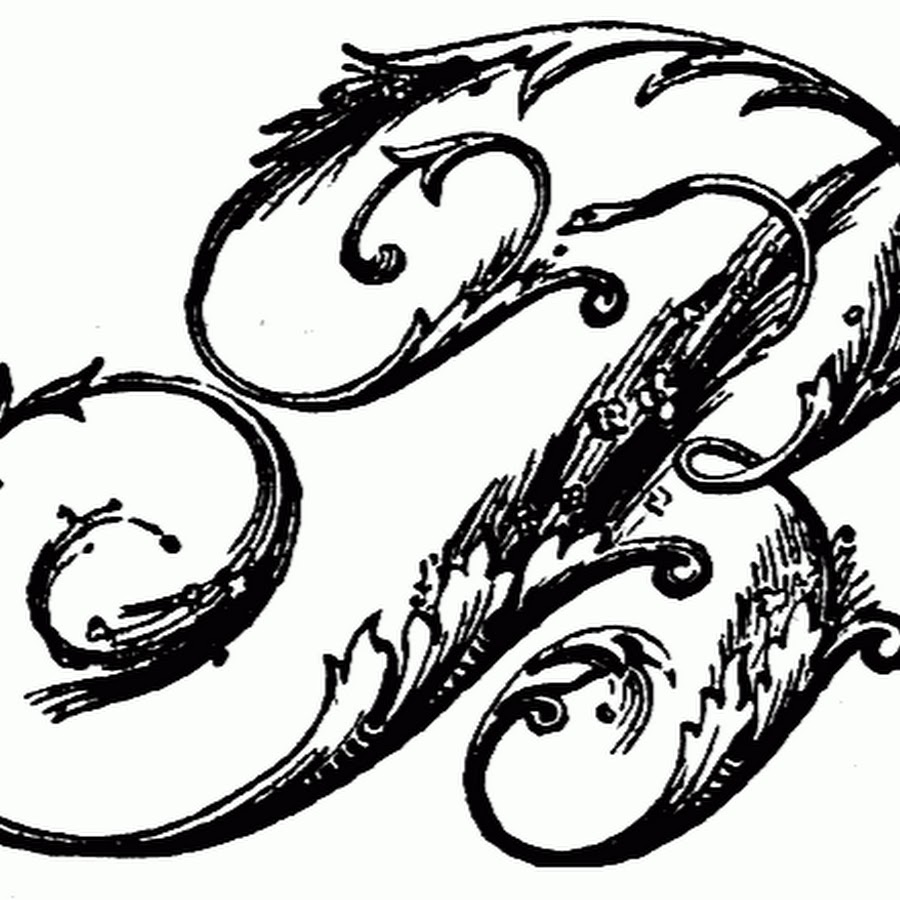
Вензельные шрифты русские: Рукописные русские шрифты
Русские декоративные шрифты XIX в.
* Шрифт 1812 года словолитни Лемана
Шрифт С. Чехонина * Инициальный шрифт С. Пожарского * Антиква орнаментированная * Обложка И. Кричевского
Инициальный шрифт Г. Фишера
Титульный шрифт С. Телингатера * Версалы О. Менхарта
Букман * Малый ленточный (Г. Кликушин)
Шрифт Б. Маркевича * Шрифт О. Менхарта * Оля (Г. Кликушин) * Обложка В. Милашевского
Антиква фигурная * Шрифт Виллу Тоотса
Витебский светлый (Г. Кликушин) * Витебский жирный (Г. Кликушин)
Витебский средний (Г. Кликушин)
Барс (Г. Кликушин) * Гранит (П. Кузанян) * Арабский * Обложка Н. Ильина
Украинский
Дракон (китайский) * Карнас * Нимфик * Титульный лист Д. Бисти
Ринглет
Бланшард * Юбилейный * Инициалы Г.
Кликушина * Суперобложка В. Фаворского
Давида
Орбита * Эксман * Велам * Обложка Г. Рифтина
Ориенте
Роберта * Гобо * Герольд (Н. Бертольд) * Итальянский (стилизация Г. Кликушина)
Чебурашка (Г. Кликушин)
Контдаун * Итальянский * Волна * Суперобложка В. Фаворского
Боттленек * Египетский декоративный
График (Э. Шнейдлер) * Пиноккио * Обложка Б. Шварца
Жетон
Увага (Г. Кликушин) * Фигурный (Г. Кликушин)
Сальто (К. Гофер)
Фигурный * Рукописный (Л. Раппопорт) * Каллиграфический * Обложка С. Пожарского
Каллиграфический
Рустика * Шрифт В. Воронецкого * Инициальный шрифт С. Телингатера * Л. Хижинский
Курсив И.
Жихарева (прописной) * Курсив И. Жихарева (строчной)
Лион курсив вензельный * Каллиграфический
Курсив вензельный
Импульс (П. Циммерман) * Бальзак (И. Бьёланд) * Шрифт Н. Пискарева * Обложка В. Лазурского
Шрифтовая композиция Виллу Тоотса
Дерби (Г. Ланге) * Шок * Дерби (прописной) * Дерби (строчной)
Антиква инициальная (Г. Кликушин)
Рондо * Шрифтовая композиция И. Гусевой
Рондо (П. Реэвеер) * Титульный лист С. Телингатера
Текст поздравительного адреса (X. Керсна) * Шрифтовая композиция Виллу Тоотса
Текст поздравительного адреса (П. Реэвеер)
Раффин (X. Кригер) * Курсив барокко (С. Кончев)
Текст поздравительного адреса (П. Лухтейн)
Каллиграфический (гарнитура) * Обложка К.
Ганнушкина
Манускрипт инициальный * Шрифтовая композиции Виллу Тоотса
Курсив * Тайм-скрипт (Г. Трумп) * Рваная кисть (Виллу Тоотс) * Обложка Виллу Тоотса
Редис
Экспресс (В. Гениш) * Редис сигнал
Редис курсив
Круглая кисть * Шрифтовая композиция Г. Кликушина * Солемнис * Обложка С. Телингатера
Круглая кисть
Круглая кисть * Обложка Г. Кликушина * Готический (фрактура) * Готический (фрактура)
Готический (текстура)
Готические инициалы * Фрагмент обложки Г. Кликушина
Готический (фрактура)
Готический текстовой * Готические инициалы * Готический швабахер * Обложка Г. Кликушина
Готический (фрактура) * Готический (фрактура)
Готический (канцлей)
Пропорции римского капитального шрифта
Построение антиквы Л.
Пачоли * Построение антиквы Л. Пачоли * Построение антиквы А. Дюрера (Е. Белуха) * Построение антиквы А. /Дюрера (Е. Белуха)
В былые времена монограммы формировались из инициалов важных людей и вшивались в на их одежде пышные каллиграфические надписи.Bellissima Script дает вам все восхитительные взмахи и взмахи, которые вам могут когда-либо понадобиться при разработке логотипа с монограммой в элегантном, утонченном стиле барокко. Bellissima Script не только источает класс, это отмеченный наградами шрифт от Алехандро Пола, который помог его основателю Sudtipos сделать себе имя в начале 2000-х годов.